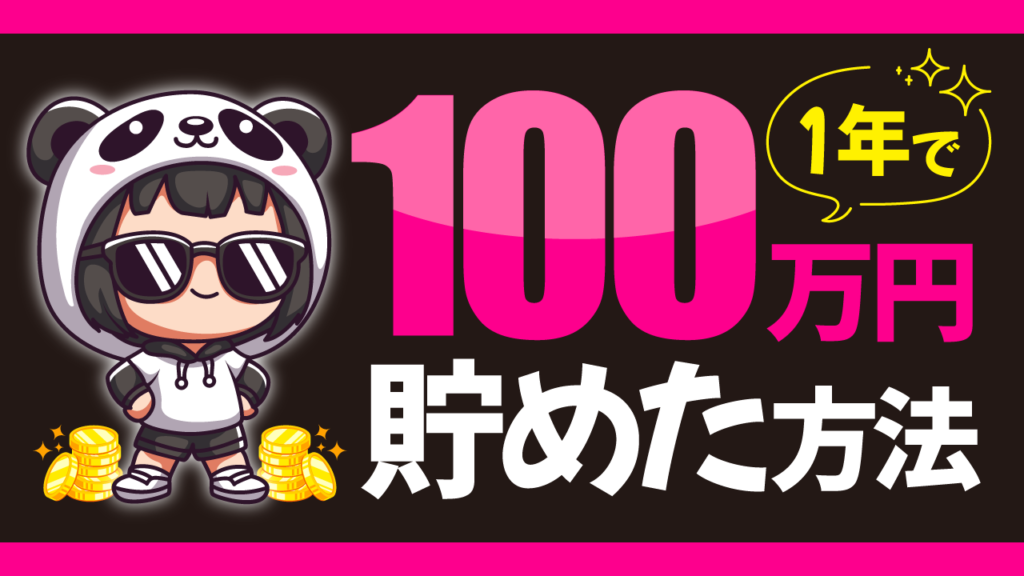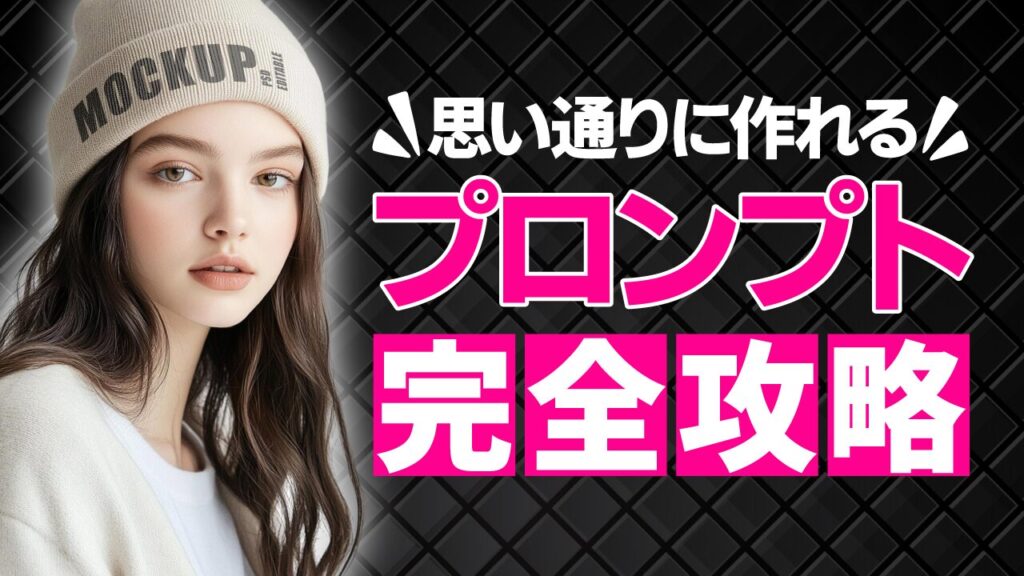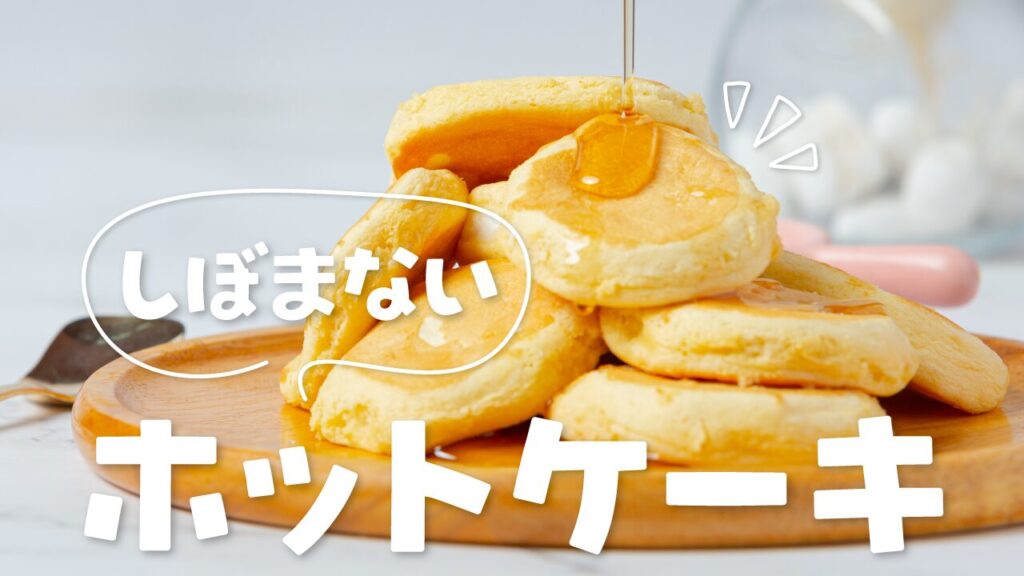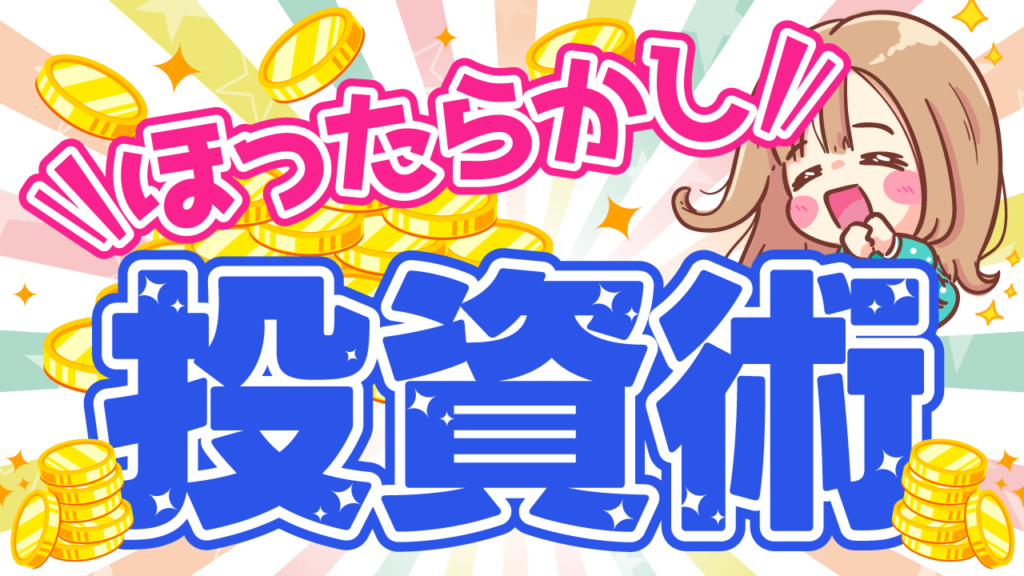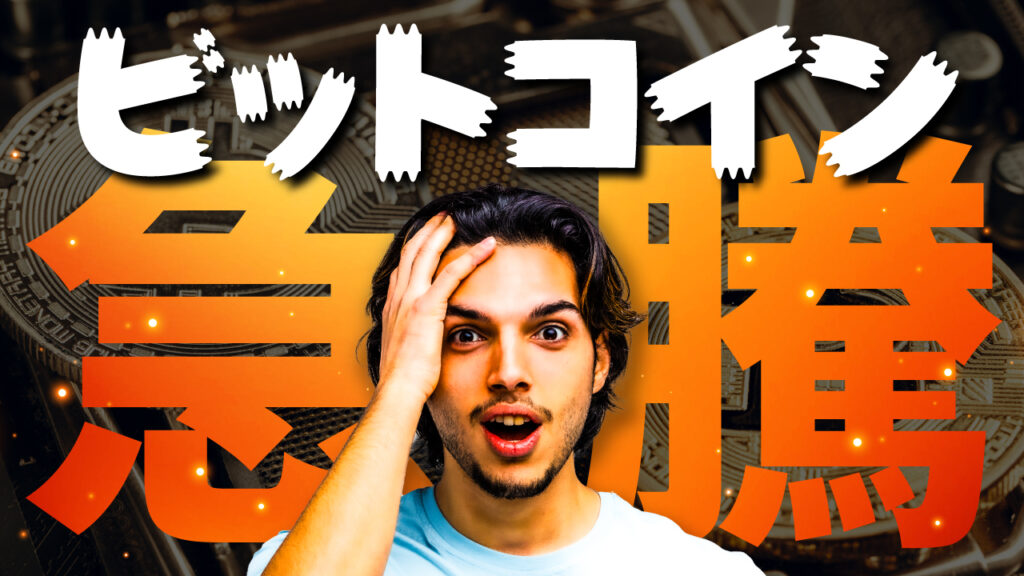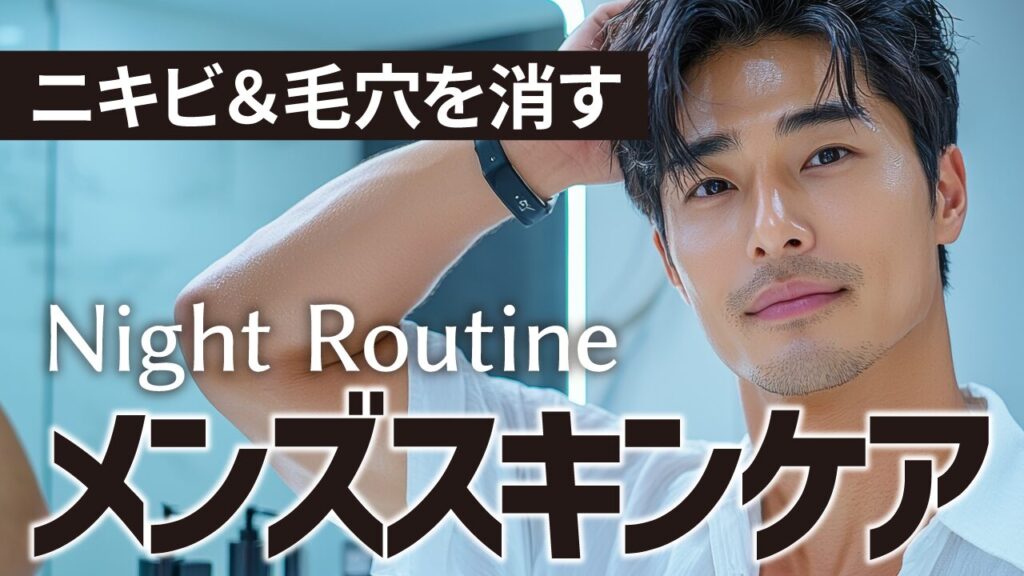
サムネイルは動画の第一印象を決める大切な要素です。フォント選び1つで視聴者に与える印象は大きく変わります。
源ノ角ゴシック(Noto Sans Japanese)
ピンクの背景に、ピンクのレギンスを履いた女性の後ろ姿を配置したフィットネス系YouTubeサムネイルの作例。『骨盤の締め方』というタイトルにフリーフォントの『源ノ角ゴシック(Noto Sans Japanese)』を使用しています。(サムネイルデザイナーおもち制作)
※『たった〇分』は源ノ明朝、『3』は源暎ラテミンを使用。
源ノ明朝(Noto Serif Japanese)
青い瞳が印象的な女性の顔のアップに、『感情操作 心の動きをコントロールする』という文字を重ねた心理学系YouTubeサムネイルの作例。フリーフォントの『源ノ明朝(Noto Serif Japanese)』を使用しています。(サムネイルデザイナーおもち制作)
※『心の動きをコントロールする』はHGP教科書体を使用。
LINE Seed JP
編み込みでアップスタイルにまとめた女性の後ろ姿の写真に、『簡単オシャレ 大人のまとめ髪』という文字を重ねたヘアアレンジ系YouTubeサムネイルの作例。フリーフォントの『LINE Seed JP』を使用しています。(サムネイルデザイナーおもち制作)
源暎Nuゴシック
ニット帽をかぶった女性の写真に、『思い通りに作れる プロンプト完全攻略』という文字を重ねたAI画像生成系YouTubeサムネイルの作例。フリーフォントの『源暎Nuゴシック』を使用しています。(サムネイルデザイナーおもち制作)
推しゴ
シロップがかけられている、木のお皿に盛られた分厚いホットケーキの写真に『しぼまない ホットケーキ』という文字を重ねた料理・レシピ系YouTubeサムネイルの作例。フリーフォントの『推しゴ』を使用しています。(サムネイルデザイナーおもち制作)
源暎ぽっぷる
こんがり焼かれたグラタンの写真に『たった10分 豆腐グラタン』という文字を重ねた料理・レシピ系YouTubeサムネイルの作例。フリーフォントの『源暎ぽっぷる』を使用しています。(サムネイルデザイナーおもち制作)
VDL V7ゴシック
ショッピングバッグを持ち笑顔の男性の写真に、『アウトレットで爆買い in 御殿場 ※総額100万』という文字を重ねたショッピング・爆買い系YouTubeサムネイルの作例。フォントの『VDL V7ゴシック』を使用しています。(サムネイルデザイナーおもち制作)
※『アウトレットで』は源ノ角ゴシック、『※総額100万円』は源暎ぽっぷるを使用。
M PLUS Rounded 1c
ピザやハンバーガーなど大量のジャンクフードを前にした男性の写真に、『暴飲暴食10000kcal』という文字を重ねた大食い系YouTubeサムネイルの作例。フリーフォントの『Rounded Mplus 1c』を使用しています。(サムネイルデザイナーおもち制作)
コーポレート・ロゴ ver2
鏡の前で髪を整える肌の綺麗な男性の写真に、『ニキビ&毛穴を消す Night Routine メンズスキンケア』という文字を重ねたメンズ美容・スキンケア系YouTubeサムネイルの作例。フリーフォントの『コーポレート・ロゴ ver2』を使用しています。(サムネイルデザイナーおもち制作)
※『ニキビ&毛穴を消す』は源ノ角ゴシック、『Night Routine』は源暎ラテゴ/ラテミンを使用。
チェックポイント★リベンジ
メガネやサングラスをかけた3人の女性の写真をコラージュし、『自分に似合うサングラス』という文字を重ねたファッション系YouTubeサムネイルの作例。フリーフォントの『チェックポイント★リベンジ』を使用しています。(サムネイルデザイナーおもち制作)
※『自分に似合う』は源ノ角ゴシックを使用。
モッチーポップ
パンダのパーカーを着たキャラクターとコインのイラストに、『1年で100万円貯めた方法』という文字を重ねた貯金・節約系YouTubeサムネイルの作例。フリーフォントの『モッチーポップ』を使用しています。(サムネイルデザイナーおもち制作)
※『100』はImpactを使用。
ラノベPOP
山積みのコインと喜ぶ女の子のイラストに、『ほったらかし!投資術』という文字を配置した投資・マネー系YouTubeサムネイルの作例。フリーフォントの『ラノベPOP』を使用しています。(サムネイルデザイナーおもち制作)
※『投資術』はLINE Seed JPを使用。
源暎エムゴ
ゴミ袋と女の子のイラストに、『断捨離 残すモノの選び方』という文字を重ねた片付け・断捨離系YouTubeサムネイルの作例。フリーフォントの『源暎エムゴ』を使用しています。(サムネイルデザイナーおもち制作)